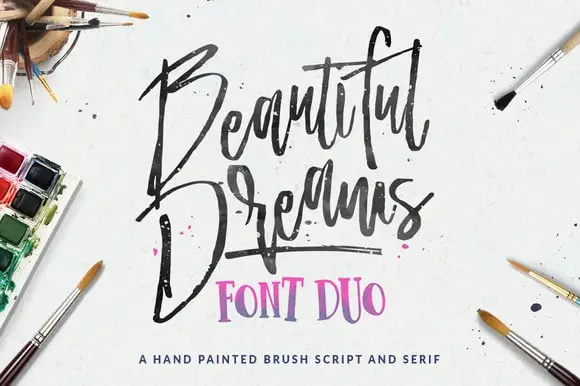
Beautiful Dreams Font – Download Grátis
Introduzimos a você a incrível fonte brush, Duo Beautiful Dreams Font. Esta criação do designer Hamilton é perfeita para seu próximo projeto de design – desde logotipos e cartões personalizados até cartazes, embalagens de produtos, merchandising, mensagens impressas ou escrita à mão. Além disso, ela se encaixa como luvas nas redes sociais, cartões de agradecimento e cabeçalhos. Com sua chamada escritura feita à mão perfeita, essa fonte mantém um toque imperfeito que é tão autêntico quanto elegante. Perfeita para aqueles projetos onde você quer um toque criativo sem comprometer o impacto visual, a Duo Beautiful Dreams Font será um recurso valioso em seu arsenal de design. Seja em cartões de aniversário ou banners do Instagram, a Duo Beautiful Dreams vai deixar sua marca mais personalizada e única.